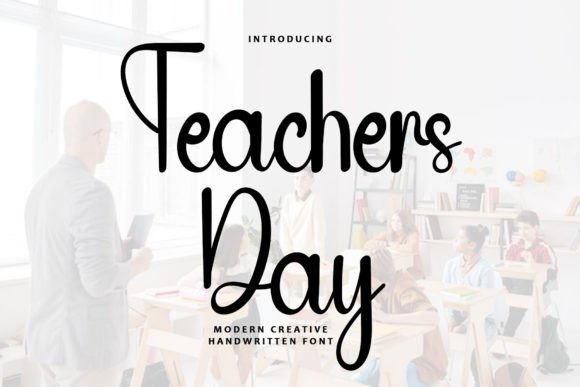
Teachers Day
Ulasan Lengkap Font “Teachers Day” – Elegância em Cada Traço
Se você está em busca de uma tipografia que una diversão e sofisticação, o font Teachers Day é a escolha perfeita. Desenvolvido com um toque artesanal, ele traz a sensação de escrita à mão, ideal para quem deseja transformar projetos digitais e impressos em verdadeiras obras de arte.
Por que escolher o Teachers Day?
- Estilo único: combina linhas fluidas e detalhes elegantes, garantindo que cada palavra ganhe personalidade.
- Versatilidade criativa: perfeito para posts no Instagram, convites, cartazes, e até mesmo para projetos de calligraphy DIY.
- Leitura agradável: embora tenha um ar descontraído, mantém boa legibilidade, essencial para títulos e chamadas de atenção.
Aplicações Ideais
- Posts de #TeachersDay nas redes sociais – destaque sua mensagem com um visual que chama a atenção.
- Convites e cartões personalizados – adicione um toque de elegância artesanal que impressiona.
- Materiais de marketing educacional – folhetos, banners e slides ganharão um ar mais humano e próximo.
- Projetos de scrapbooking e journaling – a escrita manual traz autenticidade ao seu diário criativo.
O Teachers Day não é apenas mais um font “handwritten”. Ele entrega elegância e diversão em cada curva, tornando-se a ferramenta ideal para criadores que desejam destacar suas ideias com estilo. Experimente agora e veja como seu conteúdo ganha vida!